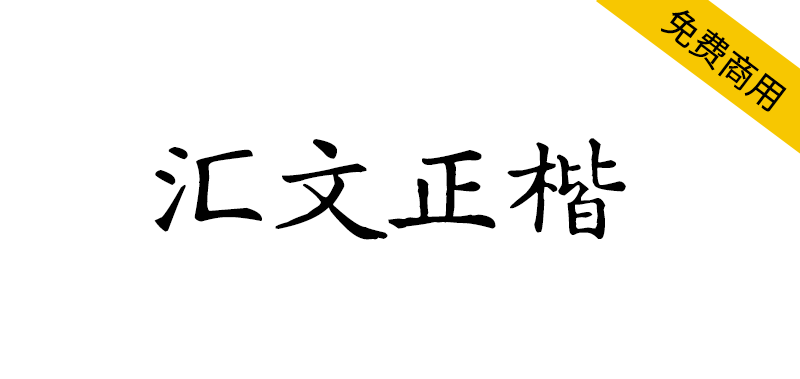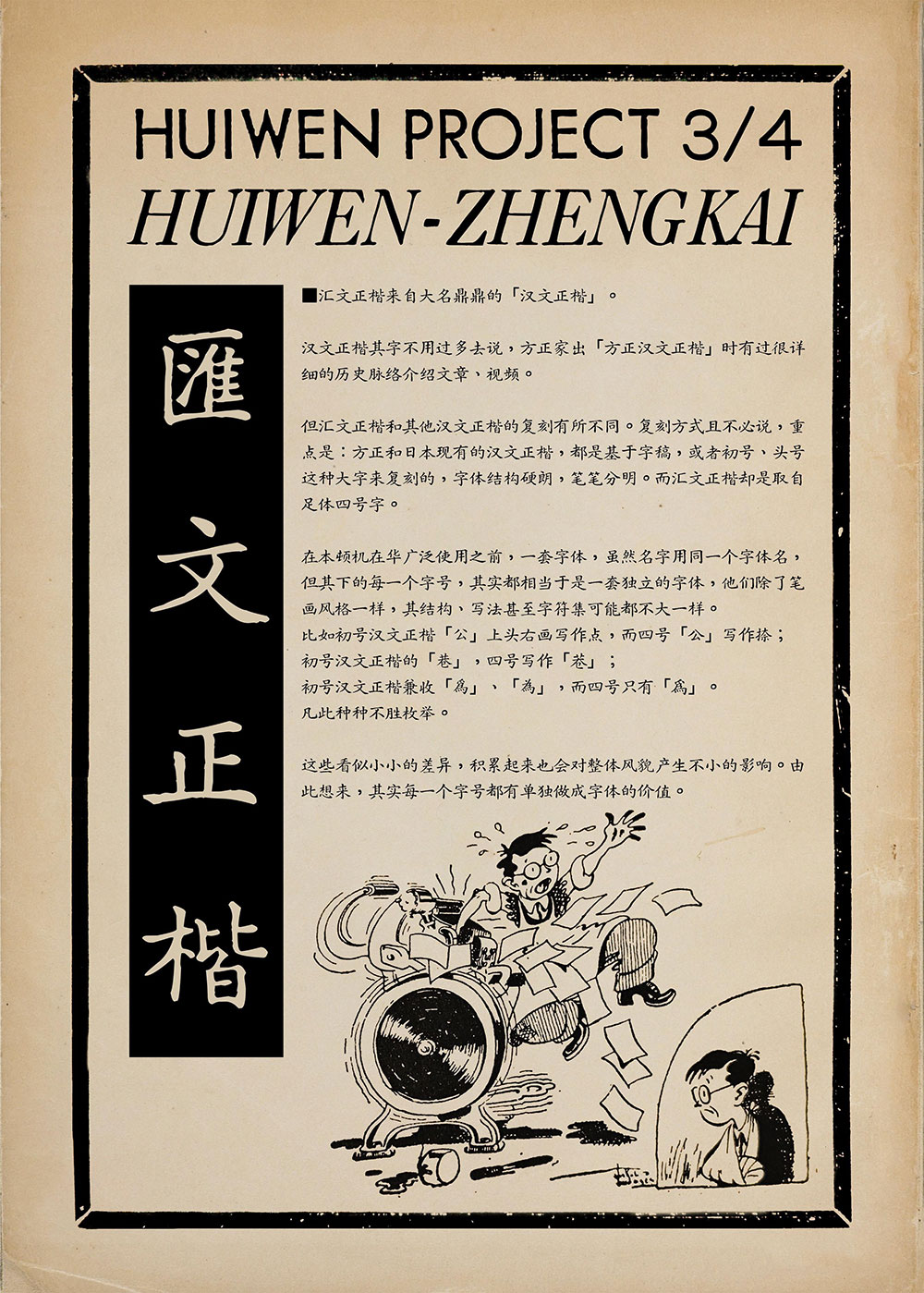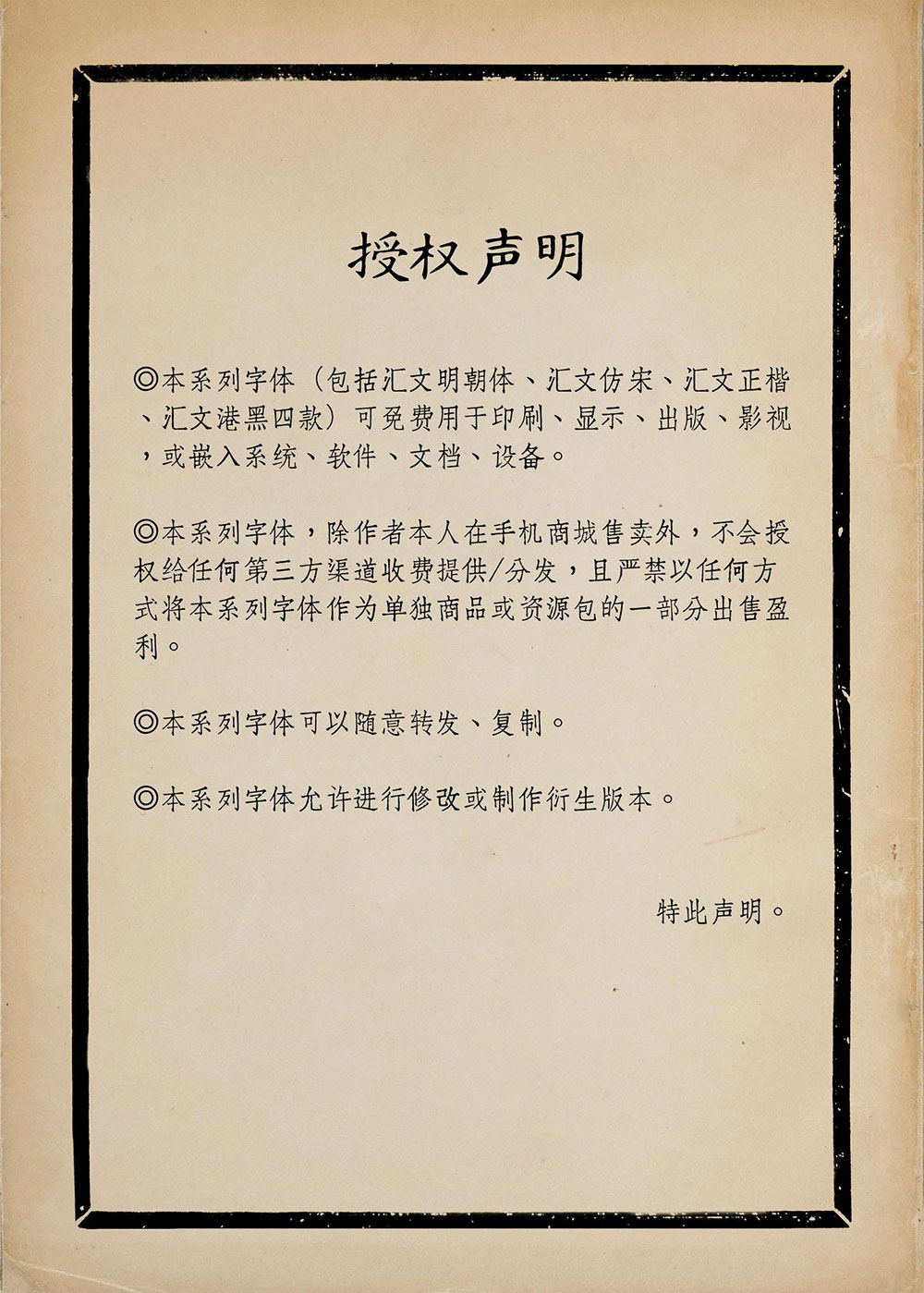
【汇文正楷】一款复古印刷效果的正楷体字体
你见过按不同字号独立设计的汉字吗?汇文正楷,源自经典的汉文正楷,却颠覆了常规复刻方式——它并非取自大字字稿,而是罕见地还原了四号活字的真实风貌。在印刷机尚未普及的年代,每个字号都是匠心独运的独立字体,细微差异成就独特韵味。这款字体不仅复刻历史,更揭开汉字排版被遗忘的细节之美。点击预览,感受复古印刷的原汁原味。
【汇文正楷】一款复古印刷效果的正楷体字体
汇文正楷来自大名鼎鼎的「汉文正楷」。汉文正楷其字不用过多去说,方正家出「方正汉文正楷」时有过很详细的历史脉络介绍文字、视频。
但汇文正楷体和其他汉文正楷的复刻有所不同。复刻方式且不必说,重点是:方正和日本现有的汉文正楷,都是基于字稿,或者初号、头号这种大字来复刻的,字体结构硬朗,笔笔分明。而汇文正楷却是取自足体四号字。
在本顿机在华广泛使用之前,一套字体,虽然名字用一个字体名,但其下的每一个字号,其实都相当于是一套独立的字体,他们除了笔画风格一样,其结构、写法甚至字符集可能都不大一样。
这些看似小小的差异,积累起来也会对整体风貌产生不小的影响。由此想来,其实每一个字号都有单独做成字体的价值